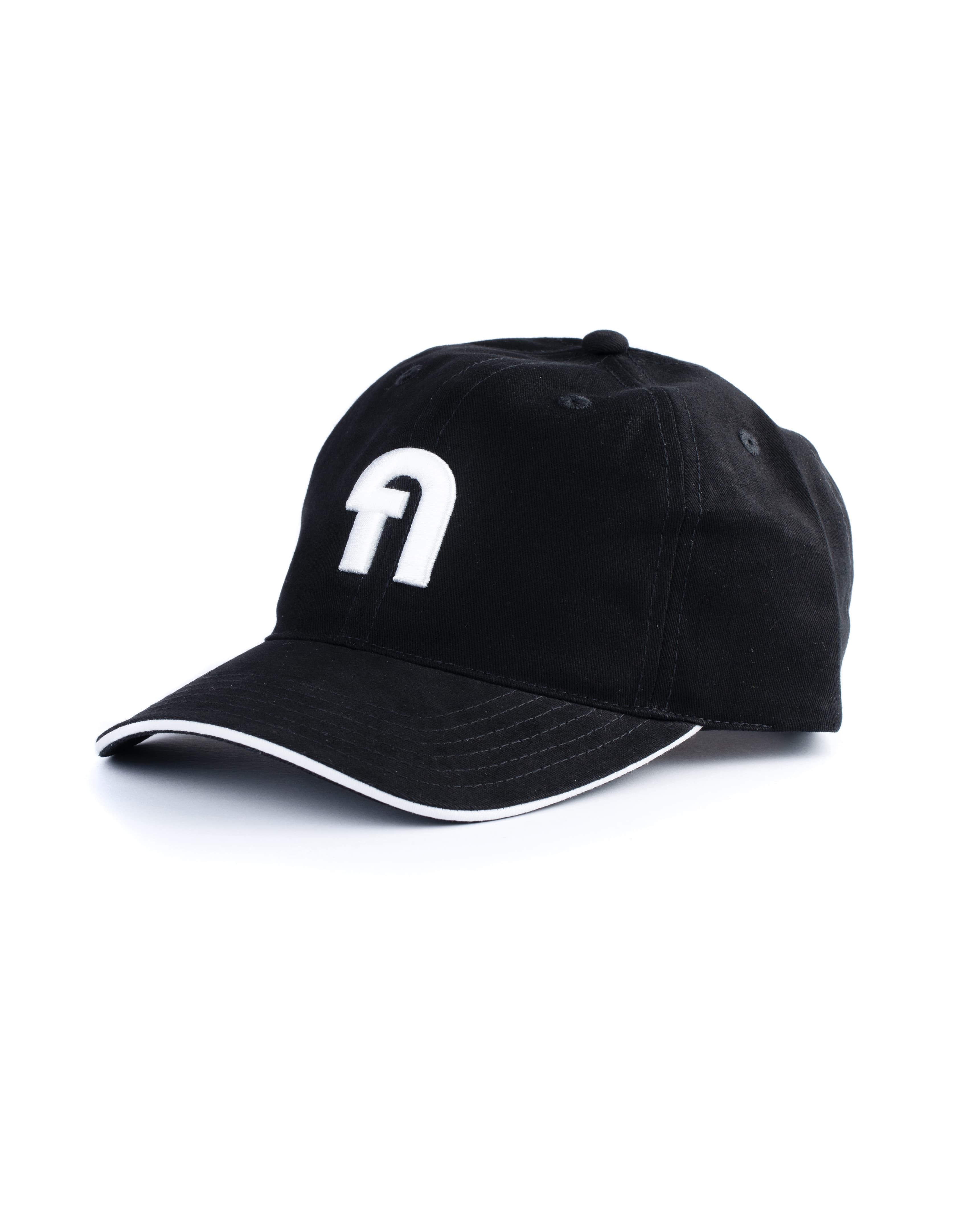
หมวก ก
หมวกปักลาย ‘ก’ ที่ตั้งใจเลือกใช้ฟอนต์ Thonglor เพื่อแสดงให้เห็นถึงอัตลักษณ์และจุดเด่นของสัดส่วนที่ค่อนข้างกว้างของแบบตัวอักษร มาพร้อมกับสโลแกน ‘WHERE FONT MEETS BRAND’ ของ คัดสรร ดีมาก ที่ใช้แบบตัวอักษรเดียวกันด้านหลังหมวก